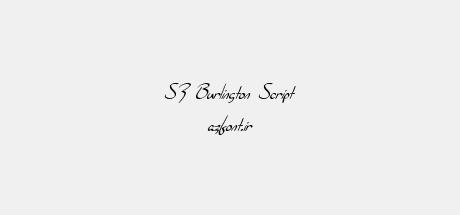
SF Burlington Script
فونت زیبای رایگان SF Burlington Script
قلم زیبای SF Burlington Script Italic از سری قلم های بسیار زیبا برای تایپوگرافی و لوگو تایپ می باشد.این قلم در وزن Italic و توسط Apostrophe طراحی و منتشر شده است.